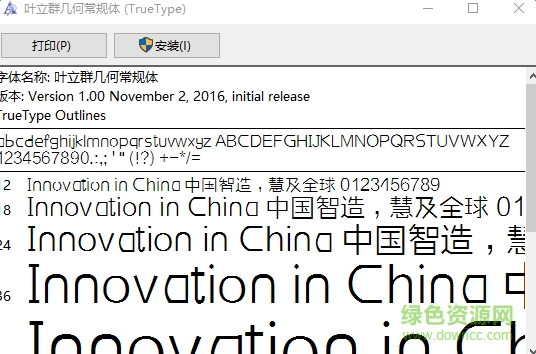
葉立群幾何常規(guī)體是一款很不錯的電腦字體,該字體寫出來的字很美觀大氣,小編知道有很多人在找這款字體已經(jīng)將字體打包好了,歡迎有需要的朋友來綠色資源網(wǎng)下載。
葉立群幾何常規(guī)體就像它的名字一樣是很規(guī)矩的,所以用于廣告設(shè)計、書本印刷還是很不錯的。